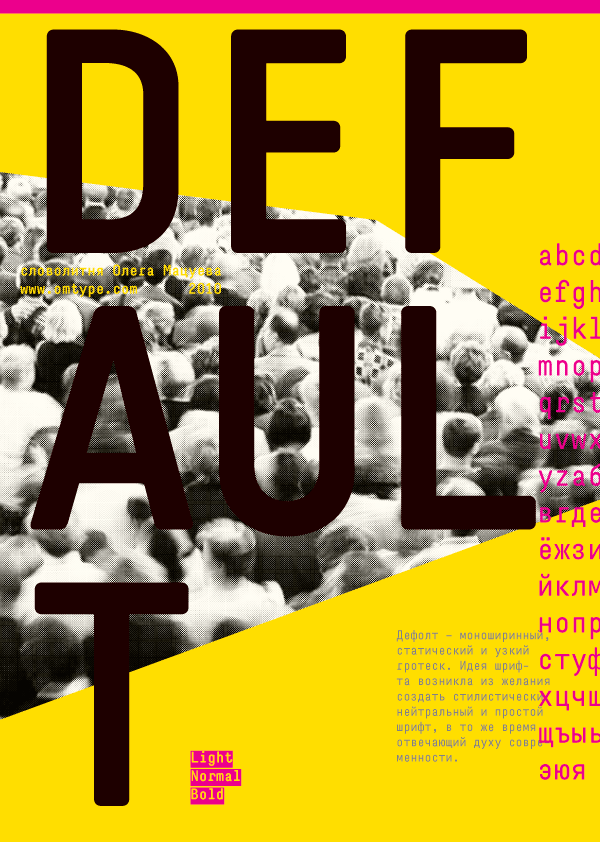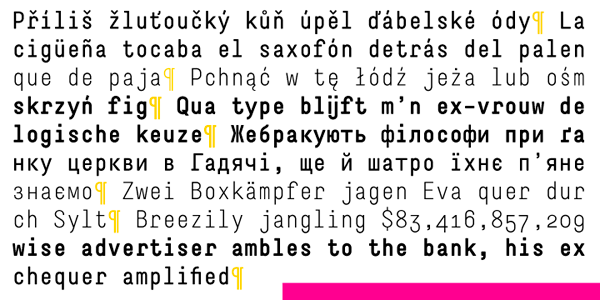
Default
Default — моноширинный статический и узкий гротеск. Идея шрифта возникла из желания создать стилистически нейтральный и простой шрифт, в то же время соответствующий духу современности. Формы букв упрощены и слегка грубоваты. Мелкие нелепости (засечки в «г», «r», форма выносного элемента «б», гельветикоподобная «а») не дают Дефолту стать модно-модульным, добавляют теплоты и наивности. А оквадраченные формы овалов и моноширинность делают набор в должной мере сдержанным и чистым.